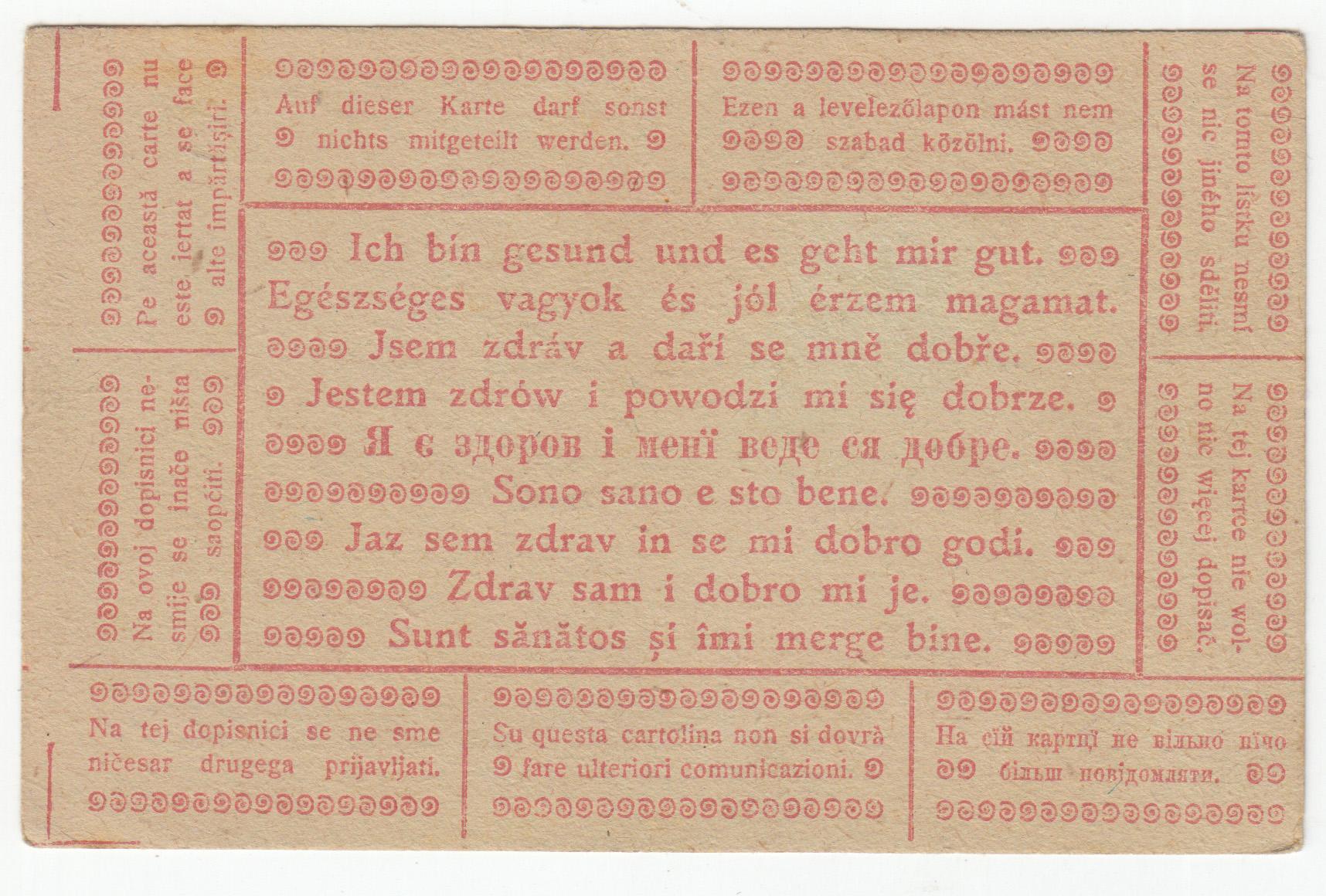
Suche Informationen zu Postkarten-Schrift aus erstem Weltkrieg
zur Recherche für ein Typedesign-Projekt suche ich Informationen zu einer Schrift, welche ich auf dem Foto einer Postkarte der österreichisch-ungarischen Armee gefunden habe. Das Foto wurde vor wenigen Tagen auf Reddit veröffentlicht.
Insbesondere interessiert mich hierbei die Bleisatz-Schrift aus der u.a. »Ich bin gesund und es geht mir gut.« gesetzt wurde.
Folgende Informationen finden sich auf Reddit in der Diskussion unter dem Postkartenfoto:
This particular postcard was sent from Croatian infantry regiment of Hungarian Royal Army - the 25th Agram Honved Infantry Regiment - in the aftermath of the Brusilov Offensive on the Galician part of the Eastern Front (from Hlybivka in Khmelnytskyi Oblast to be exact).
(»Diese Postkarte wurde vom kroatischen Infanterie Regiment der österreichisch-ungarischen Armee verschickt (dem 25ten Agram-Honved-Infanterie-Regiment), in der Zeit nach der Brussilow-Offensive im galizischen Gebiet der Ostfront; aus Hlybivka in Khmelnytskyi Oblast, um genau zu sein.«)
Keine Ahnung, welche Schrift das genau war. Halt irgendeine k.u.k.-tauglich ausgebaute Brotschrift, die gerade zur Hand war. Da stand sicher keine bewusste Designentscheidung dahinter. Warum willst/musst du das wissen?
Aber der Inhalt! Mannomann, so orwellesk war ja nicht mal die NVA!
Du solltest Dich mal durch den Seemann blättern.
Warum willst/musst du das wissen?
Ich sitze zur Zeit an der Überarbeitung eines Schriftentwurfs, der eine ganz ähnliche Grundkonstruktion aufweist und mehrere Eigenheiten der gesuchten Schrift teilt (a, e, aber auch d, b); das hat natürlich sofort mein Interesse geweckt. Ich würde einfach gerne mehr über sie erfahren und mit ganz viel Glück an ein größeres Schriftmuster gelangen. Ich hatte gehofft, dass es sich vielleicht um eine etwas bekanntere Satzschrift handelt, die mir bisher irgendwie entgangen war.
noch eine kleine Beobachtung habe ich gemacht. Die kyrillischen Lettern sind aus einer klassizistischen Antiqua, ähnlich einer Bodoni. Vielleicht könnte man auch über diese an potentielle Schriftgiessereien rankommen? Aber wie?